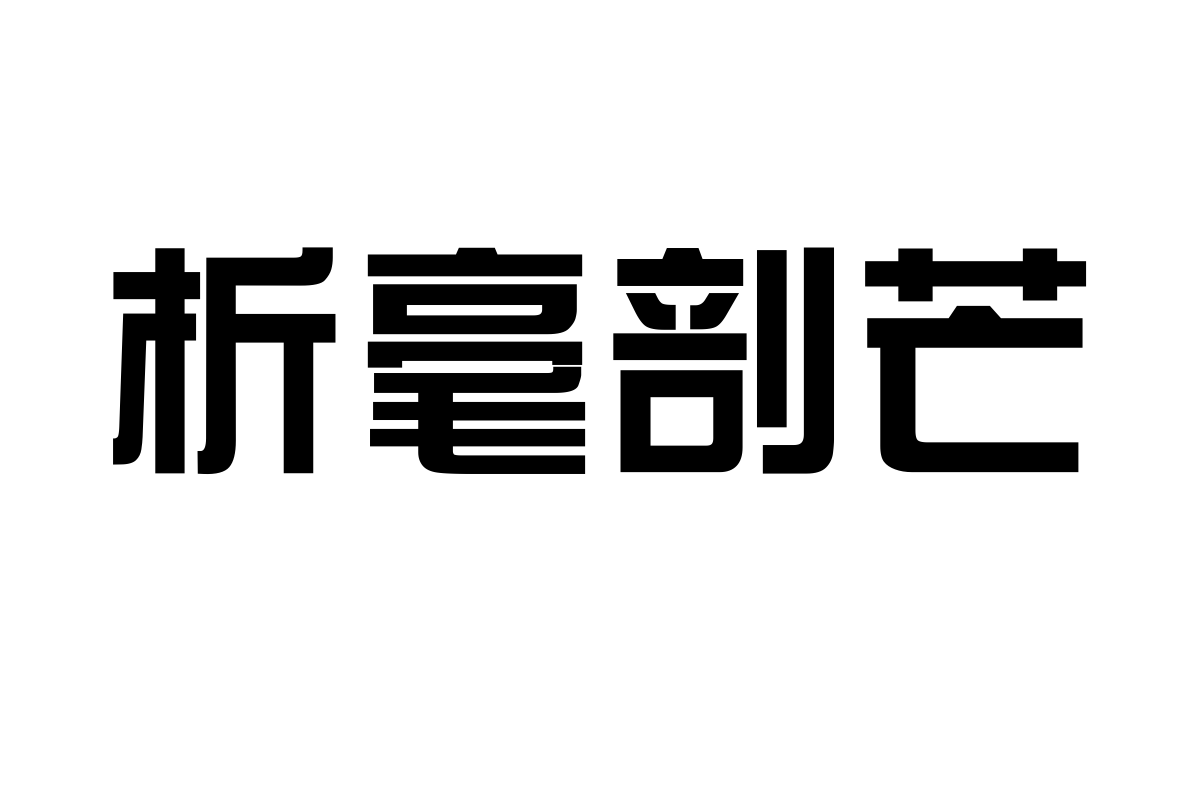
汉仪综艺体是一种中文字体,由汉仪公司设计。这款字体以其独特的风格和特点而受到广泛欢迎。它的字形结构紧凑,笔画粗细适中,给人一种简洁明快的感觉。同时,汉仪综艺体还具有丰富的字重选择,可以满足不同场景的需求。此外,这款字体还具有较高的可读性和易用性,无论是用于印刷还是电子屏幕显示,都能展现出良好的效果。总之,汉仪综艺体是一款实用且美观的中文字体,值得广大设计师和用户选择使用。